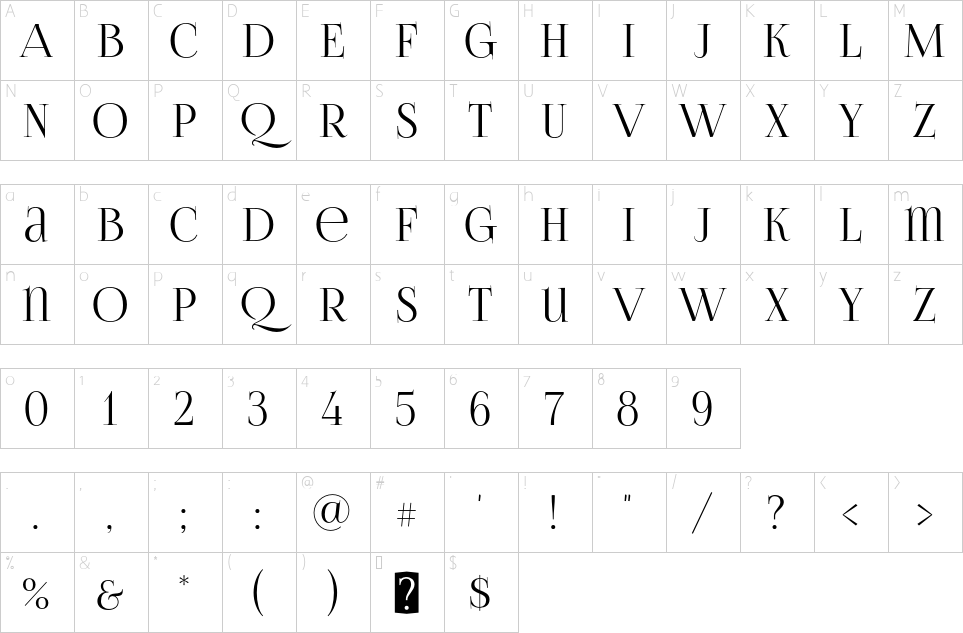
Foglihten No 06 é uma fonte elegante e moderna que combina elementos gráficos e tipográficos para criar um efeito arredondado e sofisticado. Esta fonte foi criada pela Gluk Fonts e é um dos muitos recursos gráficos que a 1001 Free Fonts oferece gratuitamente. Suas linhas fluidas e desenhos curvilíneos proporcionam um resultado gráfico envolvente, que pode ser usado em variados projetos, desde logotipos até publicações online. Download Foglihten No 06 font e experimente suas possibilidades para adicionar um toque único e moderno a seus projetos. Com sua facilidade de uso e variedade de aparência, esta fonte é um excelente recurso para designers e criativos em busca de novas opções.